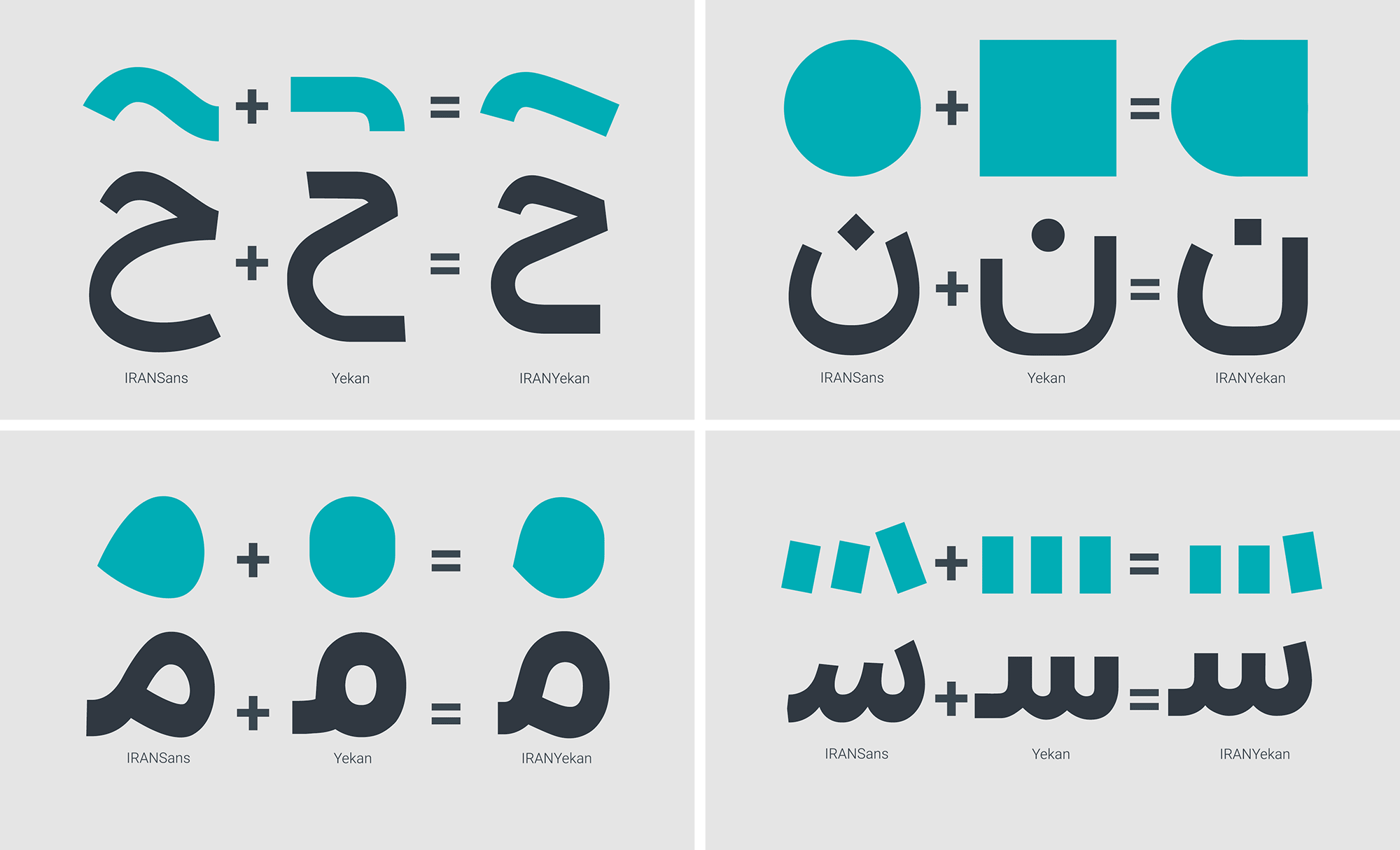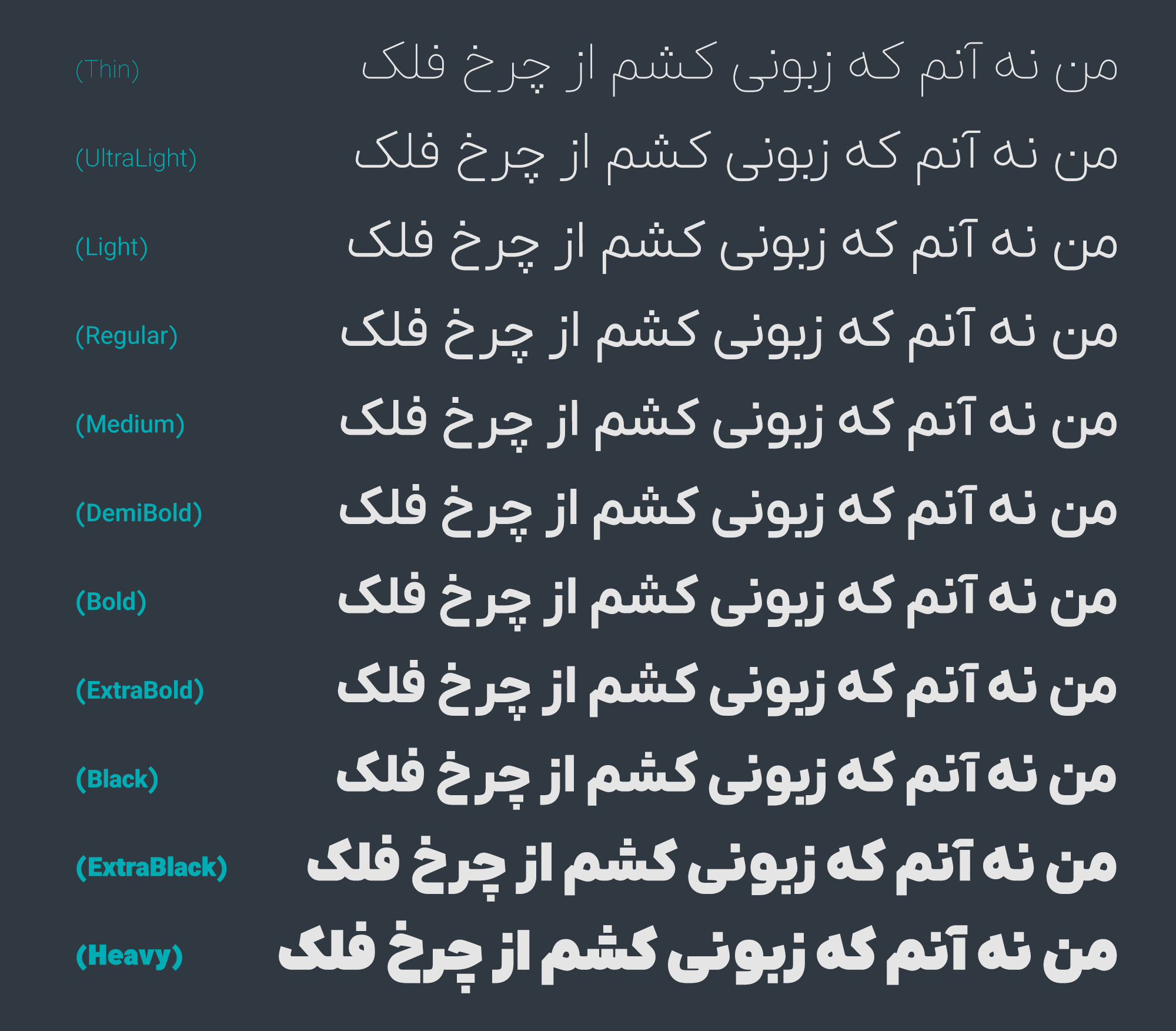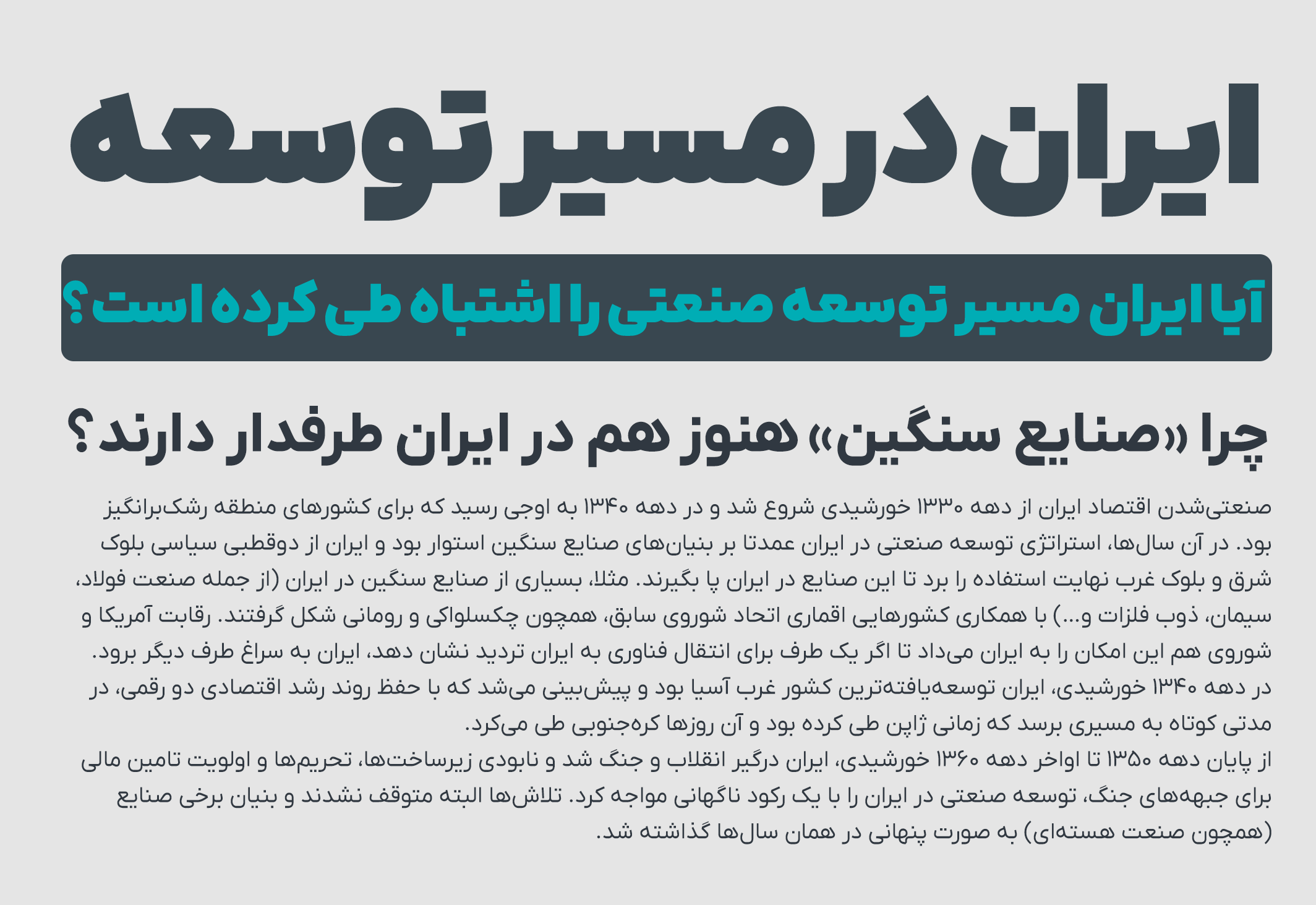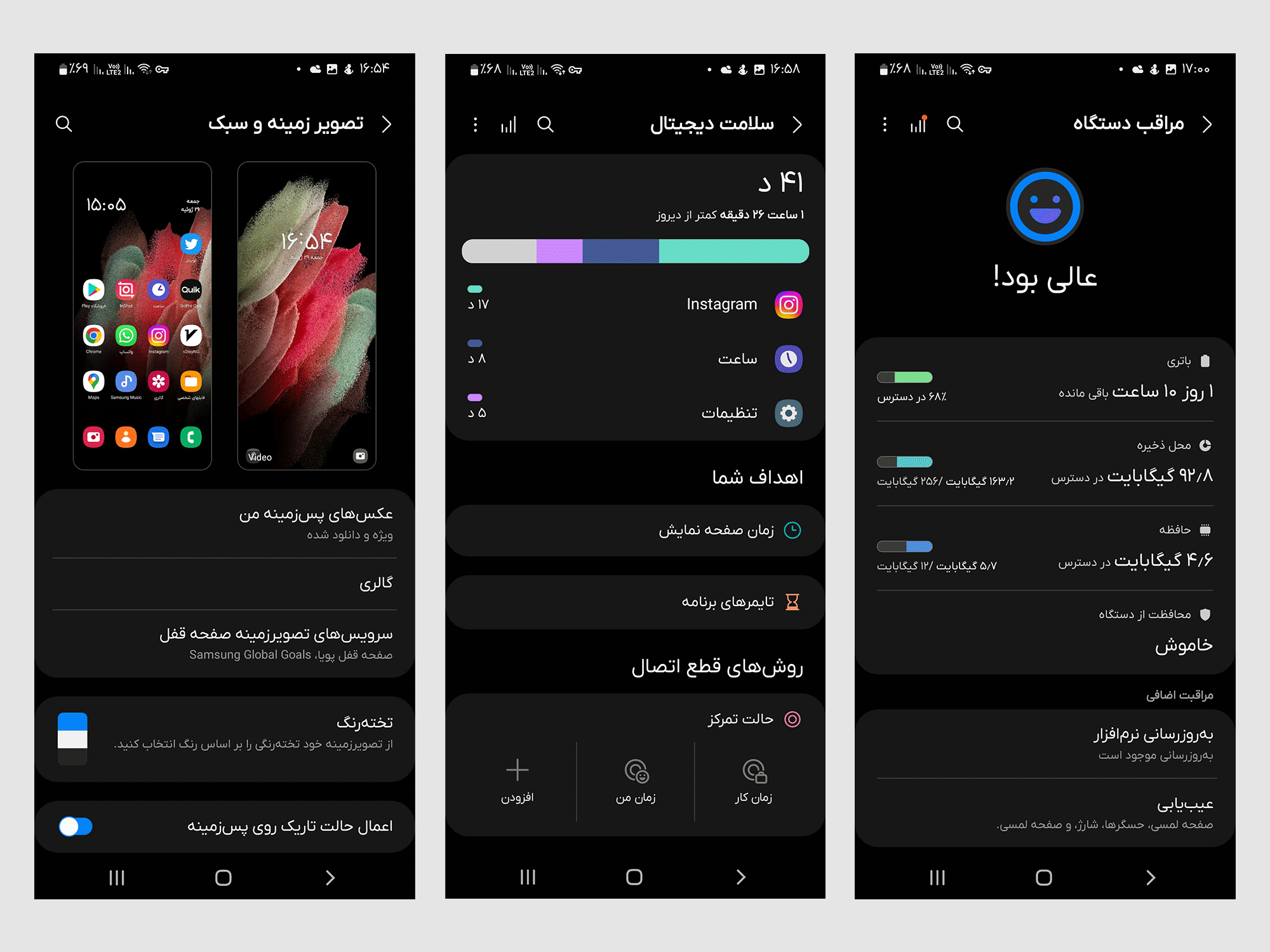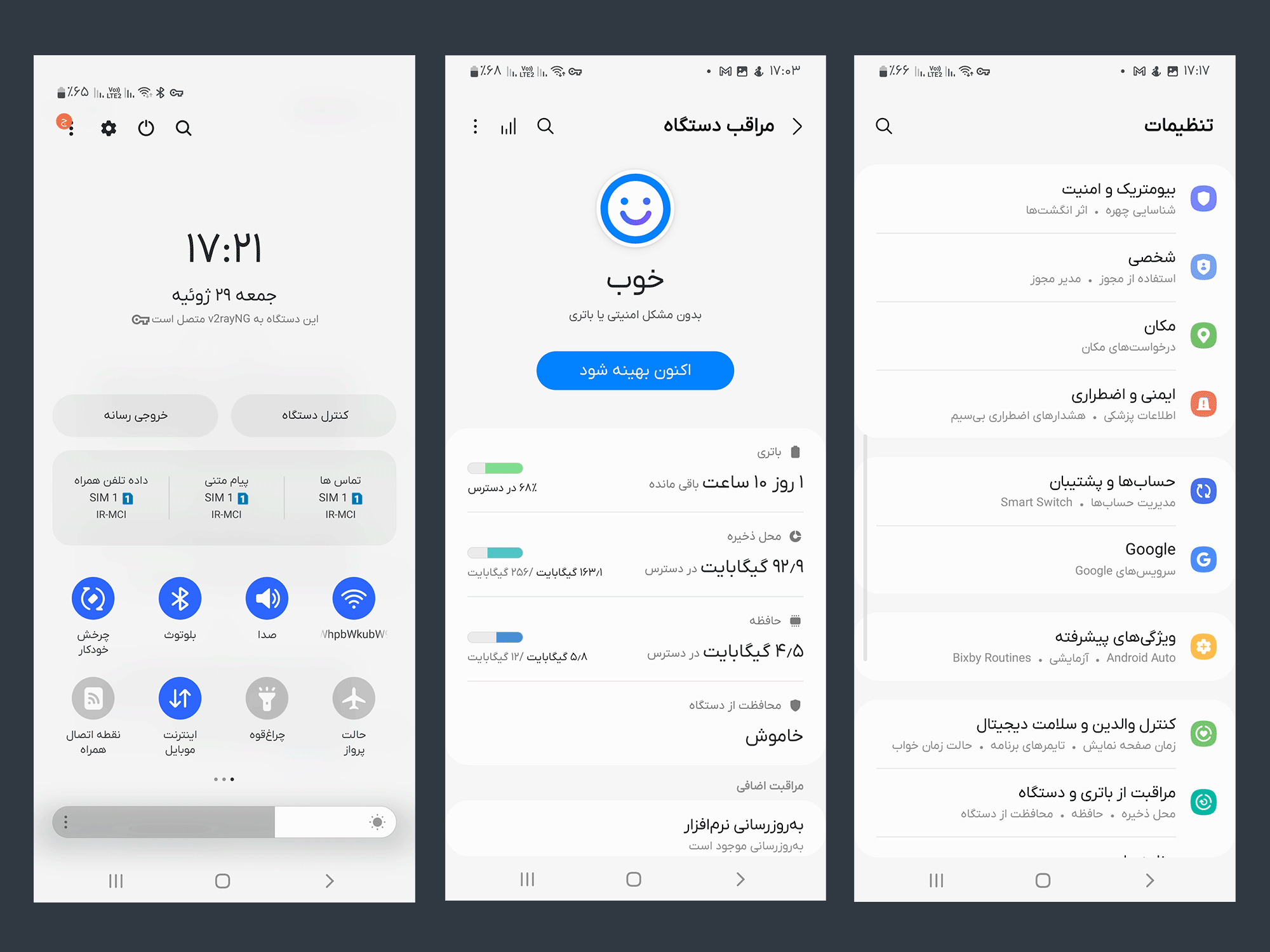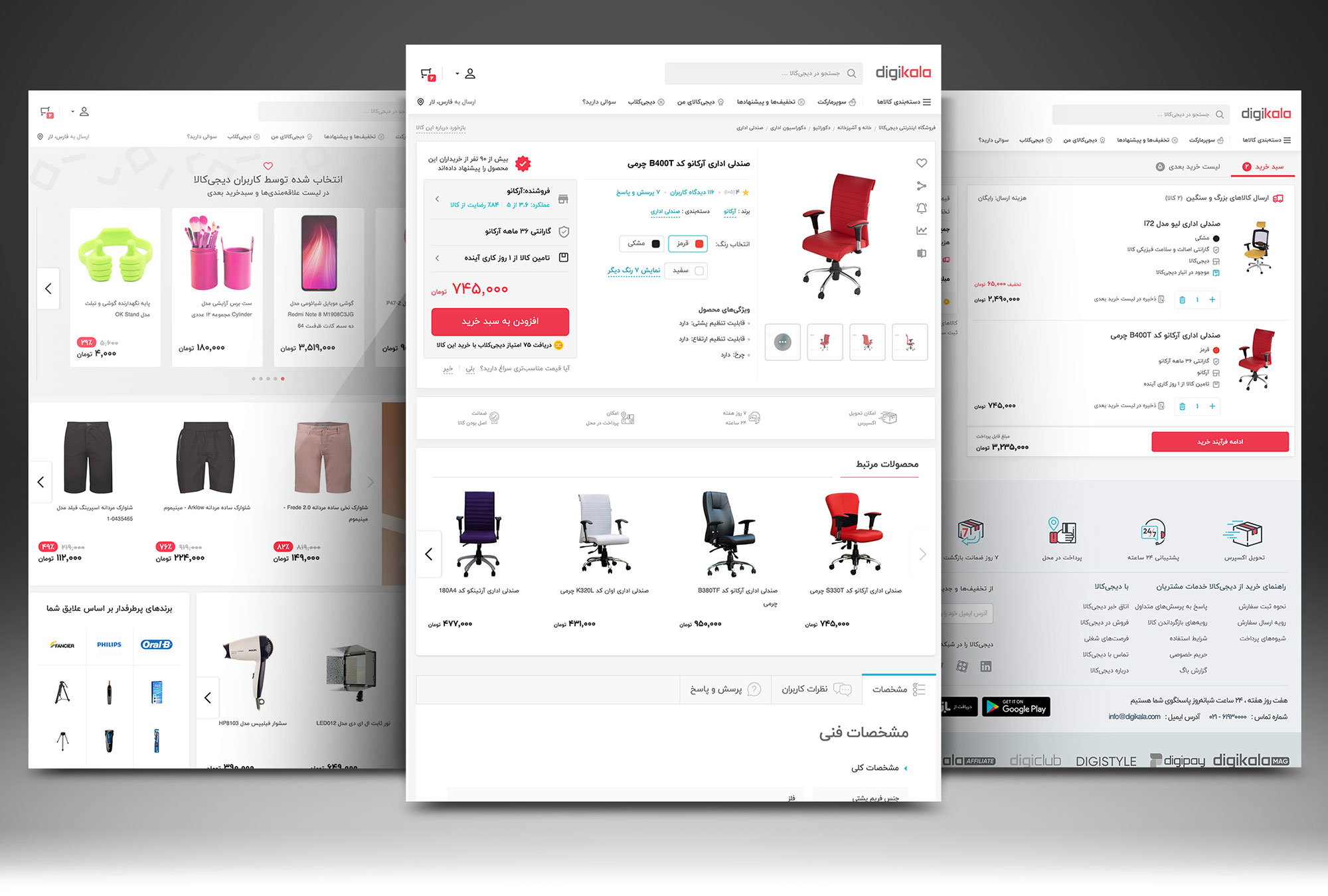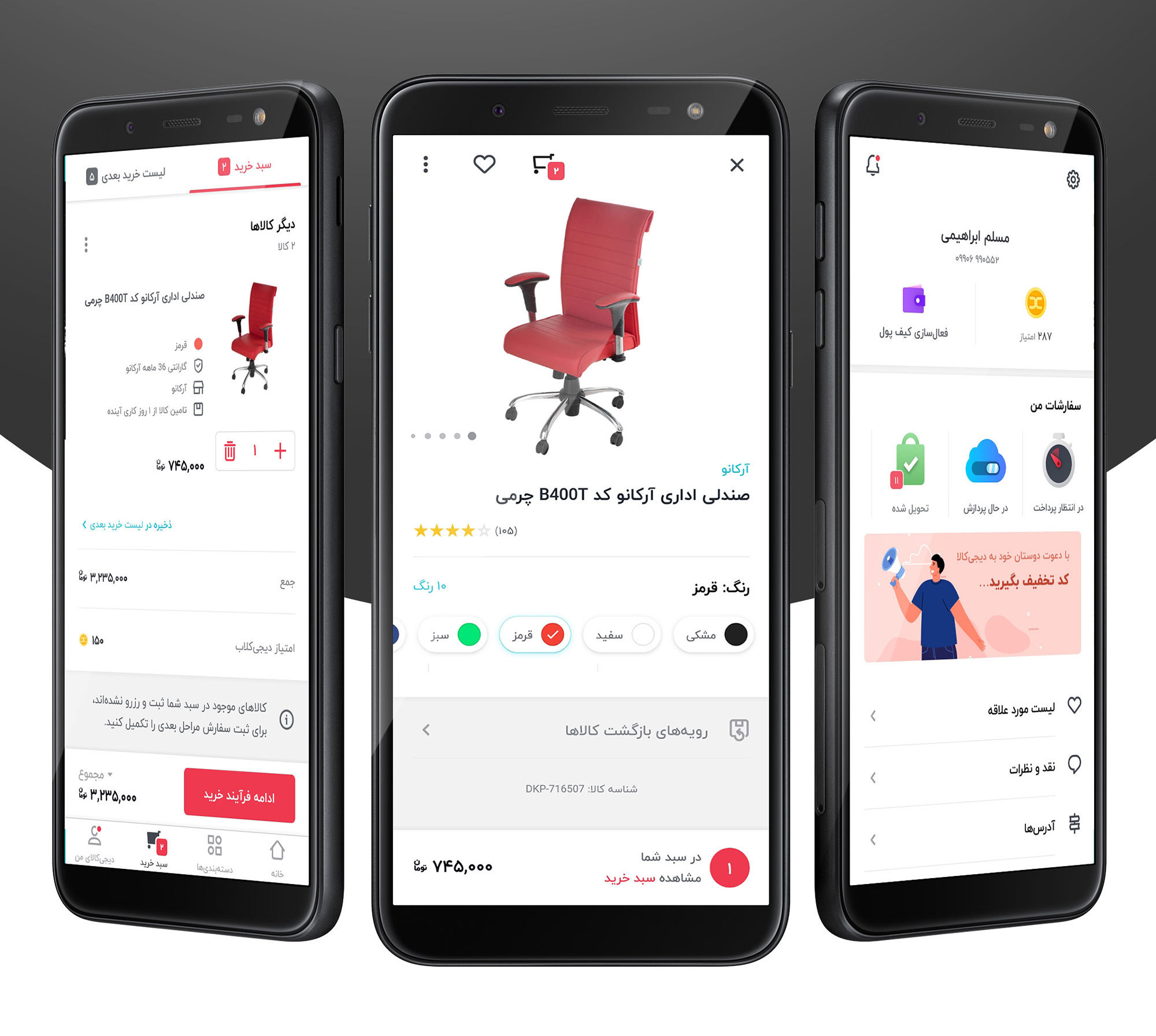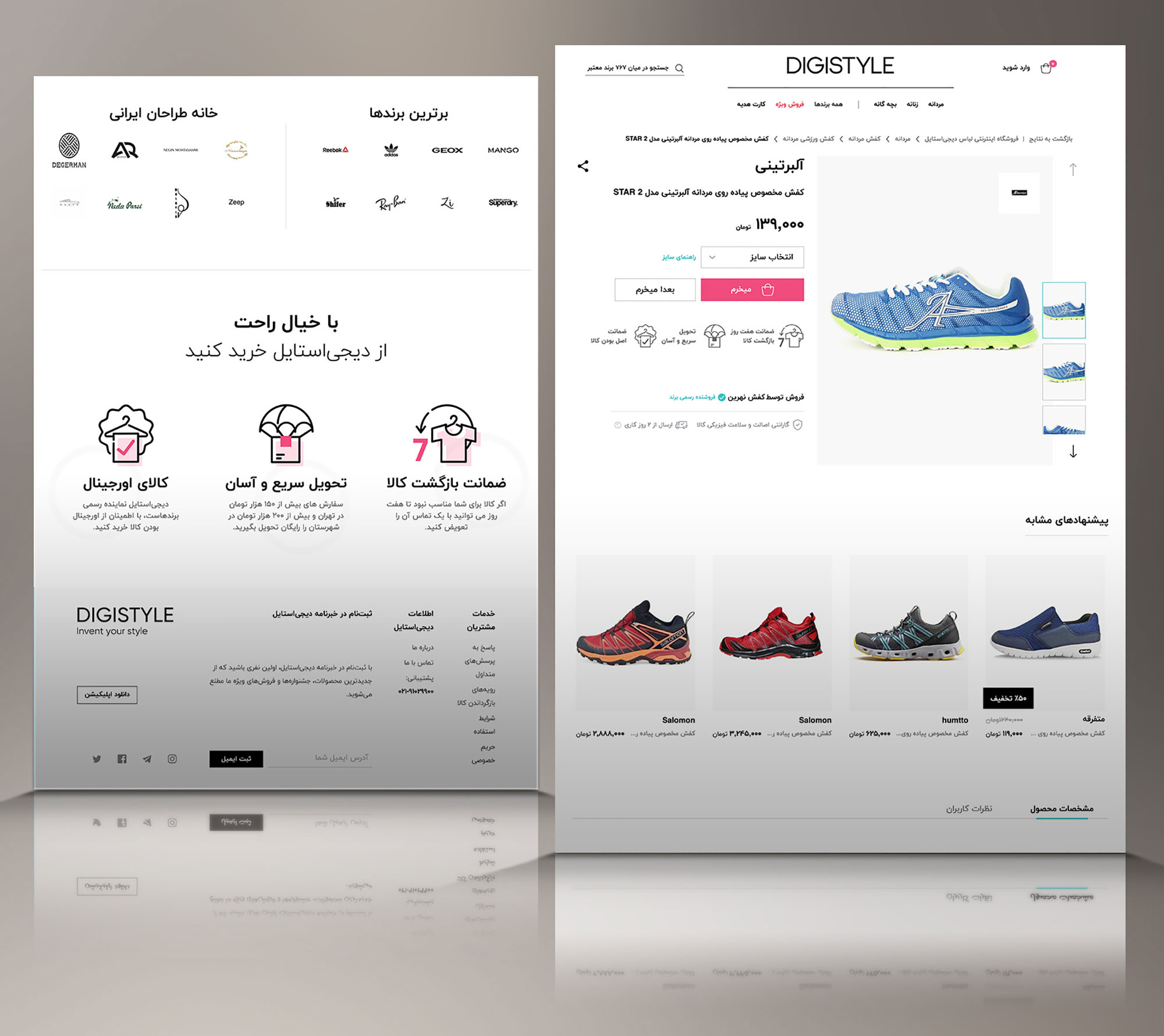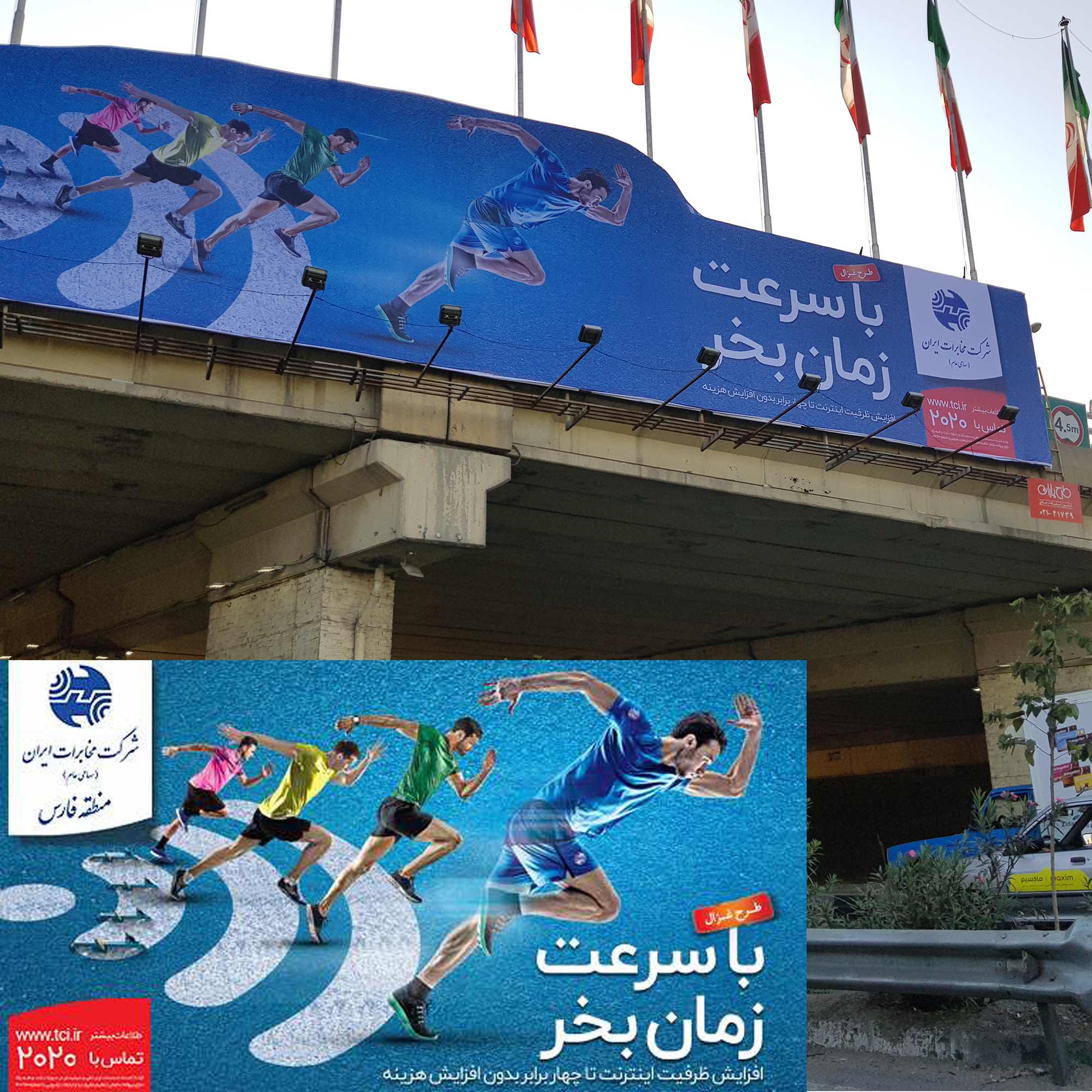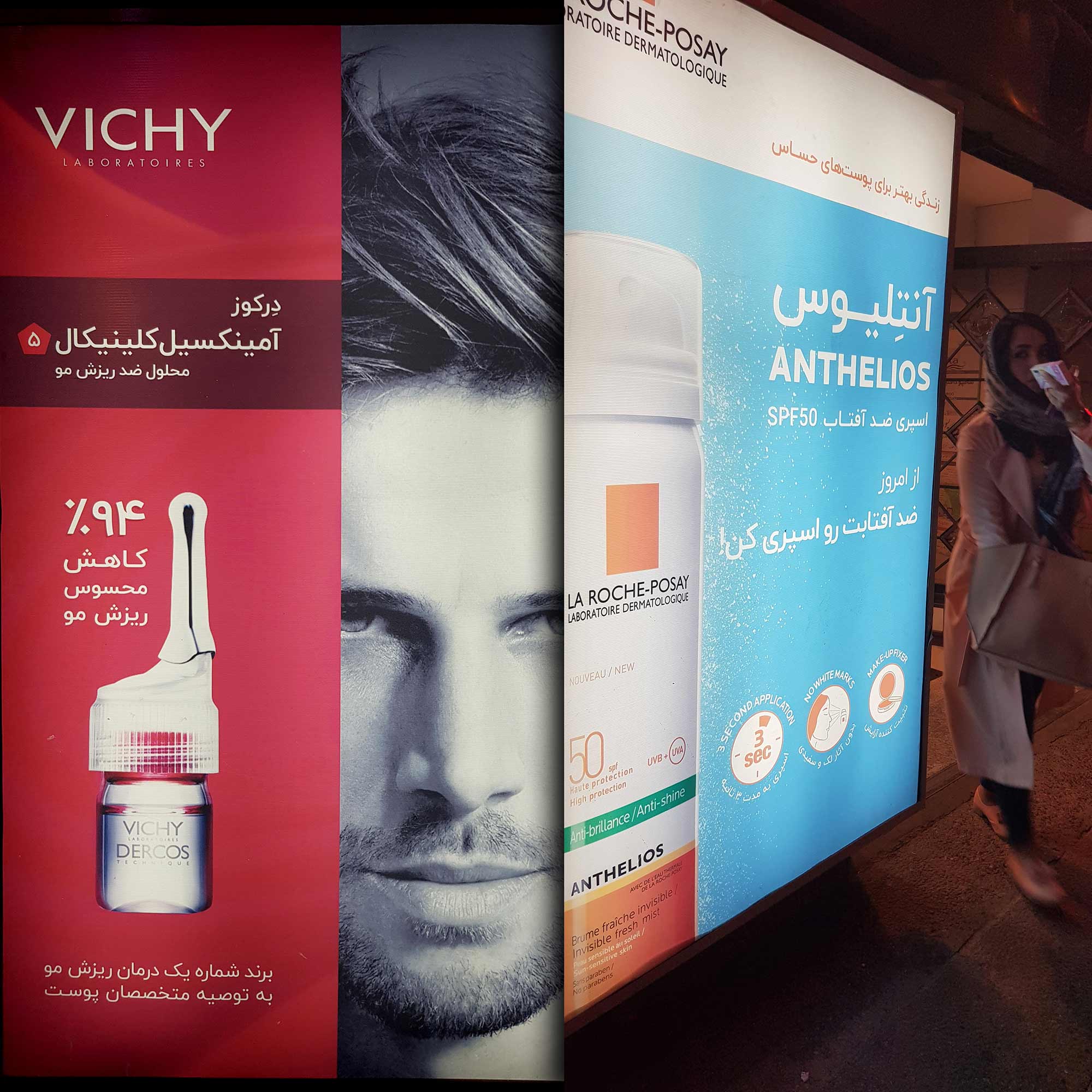
ایران + یکان = ایرانیکان
ایرانیکان شخصیتی متعادل و میانهرو دارد. اگر ایرانسنس یک دایره سیال باشد و یکان یک مربع ایستا، ایرانیکان چیزی میان این دو است.
طبق بررسی سایت فونتایران در سال ۱۳۹۵ فونتهای یکان و ایران سنس بیشترین استفاده را در طراحی رابط کاربری داشت. بنابراین مسلم ابراهیمی تصمیم گرفتیم تایپفیسی طراحی کند که شخصیتی میان این دو فونت محبوب را داشته باشد.
تنوع وزنها در فونت ایرانیکان X
ایرانیکانx یک خانواده کامل است شامل یازده وزن. این یک جعبه ابزار کامل برای طراحان ایدهآل گراست! برای رسیدن به بهترین نتیجه گاهی نیاز داریم کمی نوشته را نازکتر یا چاقتر کنیم.
شکل نقطهها در فونت ایرانیکانX
شکل نقطهها در فونت ایران یکانX از لوزی به مربع تغییر کرده است. در وزنهای پایینتر برای خوانایی بیشتر نقطهها منفصل هستند و در وزنهای بالا برای فشردگی بهتر و نمایشیتر شدن، نقطهها پیوسته میشوند.
در نسخه وریبل فونت ایرانیکان این امکان وجود دارد که شکل نقطهها را تغییر دهید. ۴حالت مختلف نقطه برای این فونت پیشبینی شده است.
ایرانیکانX وریبل (فونت متغیر)
استفاده از وریبل فونت در طراحی وب روز به روز رایجتر میشود. فونت متغیر امتحان خود را پس داده است و هم اکنون در بسیاری از سایتهای پر بازدید فارسی بدون مشکل در حال استفاده است.
Weight : این متغیر وزن (ضخامت) نوشته را تعیین میکند که حداقل آن 100 معادل وزن Thin و حداکثر آن 1000 معادل وزن Heavy است.
Dots : این متغیر شکل نقطه حروف را به ۴ حالت مختلف تغییر میدهد.
به راحتی و در هرجا اعداد را فارسی کنید.
در فونت ایرانیکانX گلیفهای اختصاصی برای ریال و تومان طراحی شده که فشرده و کوچک هستند. این گلیفها برای طراحی رابط کاربری فروشگاهی بسیار کاربردی خواهد بود.
بیشترین کاربرد فونت ایرانیکان در طراحی رابط کاربری است. در تصاویر زیر تست این فونت در محیط رابط کاربری اپلیکیشن موبایل را میبینید.
در فونت ایرانیکان IranYekanX نقطهها بصورت برنامهریزی شده در محل ایدهآل قرار می گیرند. بدون اینکه عرض حروف زیادتر شود یا فضای خالی بیش از حد پدید آید.
حروف جایگزین
اکثر حروفی که دوست دارید در فونت به عنوان جایگزین انتخابی استفاده کنید (مثل ﮧ ﮩ مدل نستعلیق و ے معکوس) حروف زبان اردو هستند.
از آنجا که فونت ایرانیکان این حروف را دارد امکان استفاده از آنها در کیبورد فارسی نیز برای شما فراهم شده است.
فونت ایرانیکان علاوه بر فارسی و انگلیسی از زبانهای عربی، کردی و اردو نیز پشتیبانی میکند.
فونت ایرانیکان در استفاده
تیمهای طراحی حرفهای از فونت ایران یکان در وبسایتها و اپلیکیشنهای پر بازدید فارسی استفاده کردهاند. وبسایت و اپلیکیشن دیجیکالا، دیجیاستایل، شیپور، روبیکا و … از جمله مواردی هستند که فونت ایران یکان را انتخاب کردهاند.
استفاده از فونت ایرانیکان در وبسایت دیجیکالا
استفاده از فونت ایرانیکان در اپلیکیشن دیجیکالا
استفاده از فونت ایرانیکان در وبسایت دیجیاستایل
استفاده از فونت ایرانیکان در طراحی وبسایت اسپارد
استفاده از فونت ایران یکان در تبلیغات
فونت ایران یکان همچنین فونت مناسبی برای هر نوع تبلیغاتی است که لازم است با تکنولوژی و زندگی مدرن مرتبط باشد.